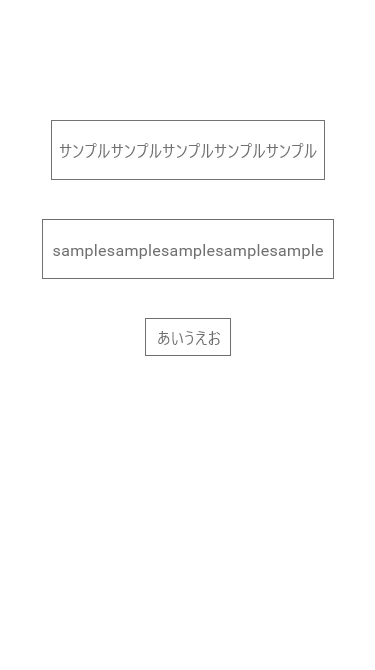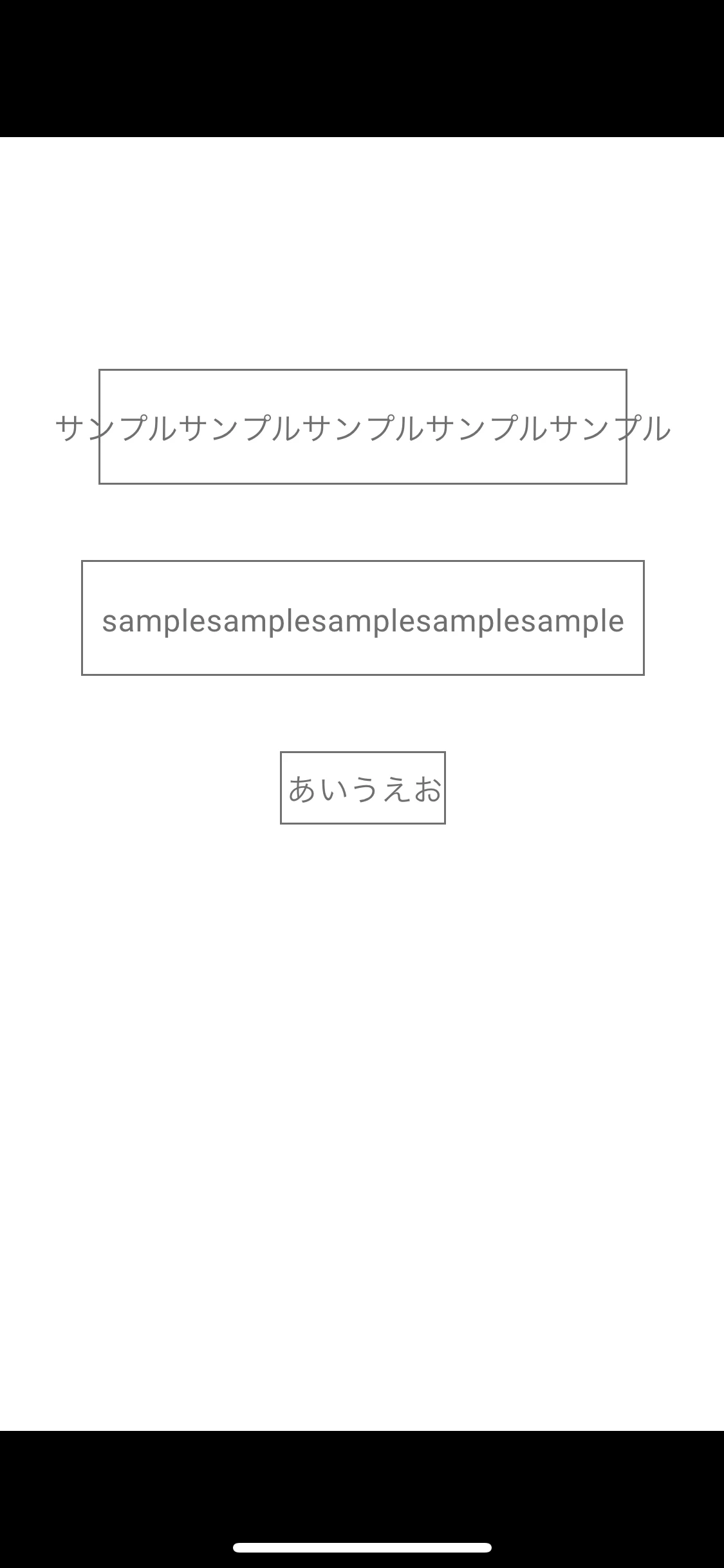
フォントのレイアウト崩れ
Windows10をつかい、XDでiphone6のアートボードでレイアウトしているのですが、iphone(19:9)やandoroid(16:9)の検証端末で表示してみると
文字が異常にレイアウトずれてしまいます。
ボタンやウィンドウに収まるレイアウトをしていたとしても、モバイルで表示させると何文字もはみ出てしまうような状態です。
ボタンとかウィンドウなどのオブジェクトは、デザインどおりに表示されてます。フォントだけです。
ただし、WindowsのPC上でのデスクトッププレビューだとフォントも綺麗に表示されます。
みなさんこういう現象おきないでしょうか?
フォントは仮でArialを使っています。初期フォントのほうがよいのでしょうか…
崩れる症状は、モバイル版のAdobe XD アプリで表示しているときということで良いですよね?
Windows版XDをお使いの場合Android版はUSBを通したプレビューが行えませんので、
クラウドドキュメントに上げた、もしくは、共有されたXDドキュメントを直接開いていると思います。
このときフォントがダウンロードできませんでした、あるいは、不足しているフォントの情報が出てないでしょうか?
USB接続と違ってクラウドドキュメントの表示では、フォントが自動的にダウンロードされるのはAdobe Fontsだけです。
Arialはとてもメジャーなフォントでありますが、Androidの標準フォントはrobotoですし、
Arialは必ずしもAndroidに載っているわけではありません。
iPhoneのほうはUSB接続のモバイルプレビューでしたら問題なく表示できるのではないかと思います。
こちらで表示した場合いかがでしょうか?
Adobe FontsからRobotoやSource Han Gothic(源ノゴシックと同じ系でわりと標準的に見えるフォント)などを
選択するのが良いと思います。
いまだに未解決でございます。
状況ですが、おっしゃるとおりモバイル版のAdobe XD アプリで表示しているときです。
クラウドドキュメントで制作しており、それを開いてデバイスプレビューしている状態です。
おっしゃるとおり「不足しているフォントの情報」がでてきており規定のフォントで表示されるとのことでした。
Adobe FontsからRobotoを使い、フォント変更してみました。
ですが現象は変わらないままのようです。
参考までに、私のパソコン(windows10)での表示・iphone(19:9)での表示、それぞれのスクショを貼ります。
XDでの制作サイズはiphone6/7/8(375×667)、教えていただいたRobotoフォントですべて中央に揃えて使用しております。
そもそも制作サイズの問題?と思い、試しにiphoneXのサイズでも確認してみましたが同じ現象でした。
こうしてよくよく確認してみると日本語、しかもカタカナの表示が特におかしいかもしれません。
▼パソコン(windows10)でのUI表示
▼iphone(19:9)での表示 ※フォントの位置が崩れている問題の状態
そしてクラウドドキュメントの表示上では、Adobe Fontsしか使えないのですね。
モリサワとかフォントワークスのフォントを使いたい場合はみなさまどうしてるのでしょうか。
クライアントの指定が他社のフォントなので、Adobe Fontsだとどうしても違いがでてしまいそうです。